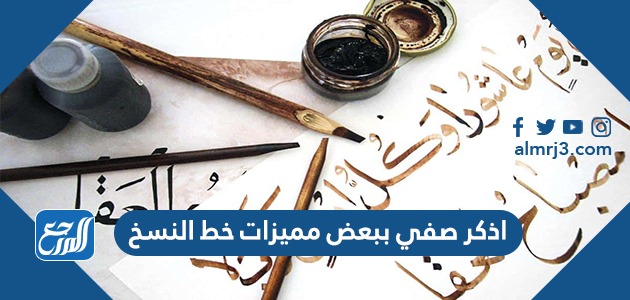
اذكر صفي ببعض مميزات خط النسخ
اذكر صفي ببعض مميزات خط النسخ من الأسئلة المقررة على الطلاب في كتاب لغتي الخالدة للصف الأول المتوسط، كما يُعتبر خط النسخ واحد من أشهر الخطوط العربية التي تستخدم في أكثر من مجال، كما يعتبر خط النسخ واحد من أبسط وأجمل الخطوط العربية، وفيما يلي عبر موقع المرجع سوف نلقي الضوء على أهم مميزات خط النسخ.
اذكر صفي ببعض مميزات خط النسخ
يُستخدم خط النسخ في كتابة الكتب الدراسية بمختلف أنواعها وأشكالها لتعليم القراءة والكتابة، وما زال يُستخدم حتى الآن، وفيما يلي سوف نتعرف على إجابة سؤال اذكر صفي ببعض مميزات خط النسخ المقرر على الطلاب كما يلي:
- تأخذ الحروف أشكالًا متعددة في رسمها.
- جمال وواضح الخط.
- سهولة الكتابة بخط النسخ.
- يمكنك قراءة الحروف بسهولة.
- يُستخدم خط النسخ في كتابة الكتب العلمية والجامعية والقصص والروايات.
- يراعي خط النسخ جميع قواعد اللغة العربية.
- تساوي حجم الأحرف في خط النسخ.
تاريخ خط النسخ
ظهر خط النسخ لأول مرة في جنوب مدينة العراق خاصة في مدينتي الحيرة والأنبار، وأول من استخدام خط النسخ هو أبن مقلة ومن بعد ذلك انتشر استخدامه إلى جميع أنحاء المملكة العربية السعودية ومن ثم ظهر بعد ذلك في عهد عمر بن الخطاب، ومن أشهر أنواع خط النسخ هو الخط الأساسي الذي استخدم في كتابة القرآن الكريم.
الخطوط العربية
تتعدد وتتنوع الخطوط العربية لتتكون من 6 أنواع أساسية وهي:
- الكوفي.
- خط النسخ.
- الفارسي.
- الديواني.
- خط الثلث.
ومن أشهر تلك الأنواع خط النسخ وخط الرقعة فقط، كما يتشابهان ويختلفان في بعض الصفات ولكن كلًا منهما يستخدمان في كتابة الكتب والقرآن الكريم.
الفرق ما بين خطي الرّقعة والنّسخ
كما ذكرنا سابقًا تشابه خط الرقعة والنسخ في بعض الأمور ويختلفان أيضًا في الخصائص، وفيما يلي سوف نلقي الضوء على أبرز الفروق بين كلًا منهما:
- كتابة حرف السين والشين في خط النسخ يمكنك كتابتها بأسنان ولكن في خط الرقعة لا يوجد اسنان للحروف ولكن تكون مطموسة.
- خط الرقعة أصغر حجمًا عند الكتابة لذلك كثيرًا ما يستخدم في الكتابة بشكل أسهل وأدق.
- يستخدم خط النسخ أكثر في مجال الطباعة ولكن خط الرقعة هو الخط الأكثر شيوعًا في الاستخدامات اليومية.